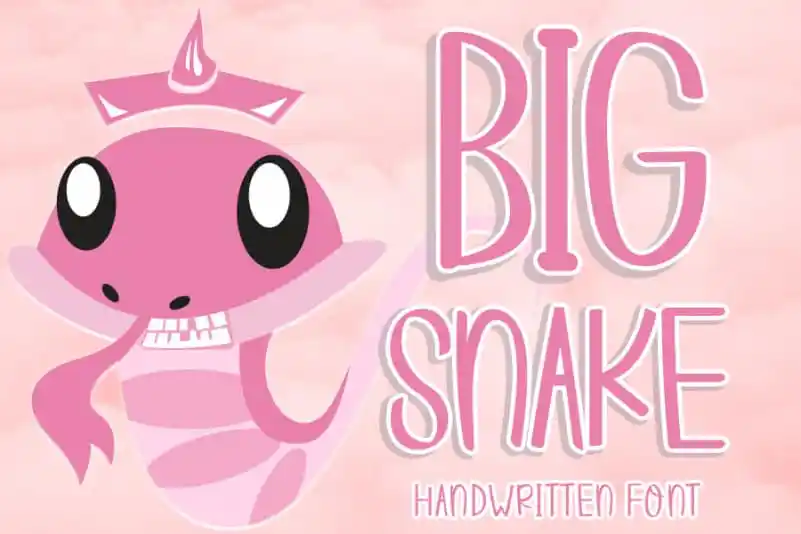
BIG SNAKE Display Font
A fonte ‘BIG SNAKE Display Font’ é uma exibição brilhante de linhas escritas a mão, mantendo seus influentes estilo de calligrafia enquanto parecem contemporâneos e frescos. Essa fonte versátil cativa ideias criativas para aplicações variadas, desde assinaturas e títulos até impressões em papelão. Com uma origem clássica na escrita a mão, o BIG SNAKE Display Font se destaca ao incorporar elementos modernos e atemporais. Seja você um designer que busca agregar um toque único em sua identidade visual ou um editor de mídia especializado em impressões, essa fonte tem algo para oferecer. Com a capacidade de personalização tão rica, o BIG SNAKE Display Font é perfeito tanto para projetos profissionais quanto para criações pessoais. Ele enriquece seu design com uma expressividade única que combina perfeitamente com os estilos modernistas atuais e suas influências clássicas. Para qualquer projeto que você esteja planejando, a fonte ‘BIG SNAKE Display Font’ é o ideal para adicionar um toque autêntico e vibrante. Seu design fluido permite uma ótima legibilidade e combinação com cores vibrantes ou tonalidades mais sóbrias de acordo com seu gosto pessoal.